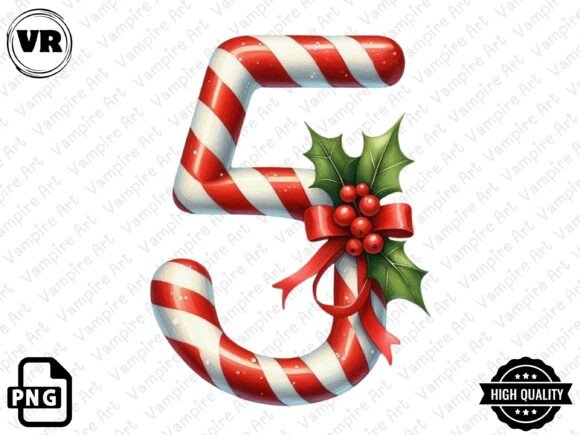
Holiday Typeface and Number Clipart PNG
Поиск подходящих элементов дизайна может быть сложным, но Holiday Typeface and Number Clipart PNG предлагает исключительную коллекцию, которая мгновенно улучшит вашу работу.
Созданный с высокой точностью, Holiday Typeface and Number Clipart PNG предоставляет чистые векторы, плавную типографику и коммерческую лицензию для вашего спокойствия.